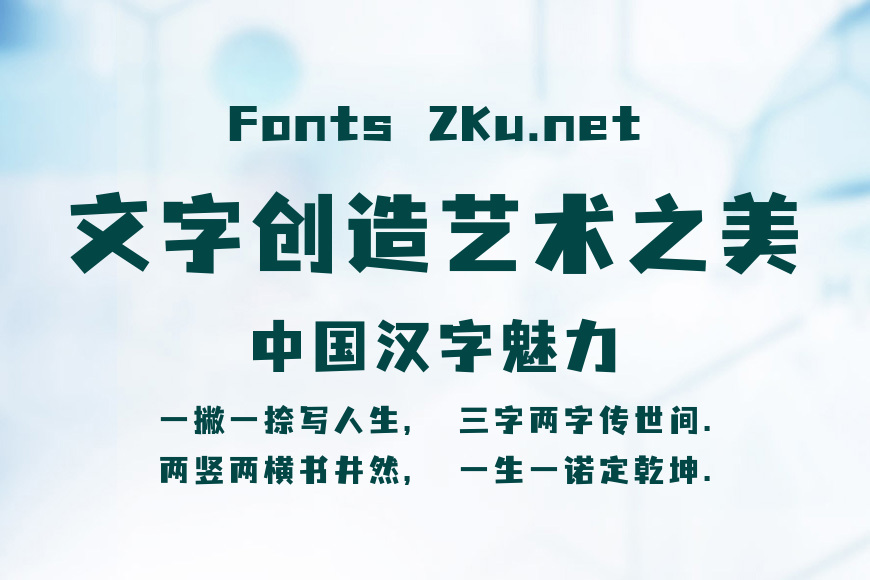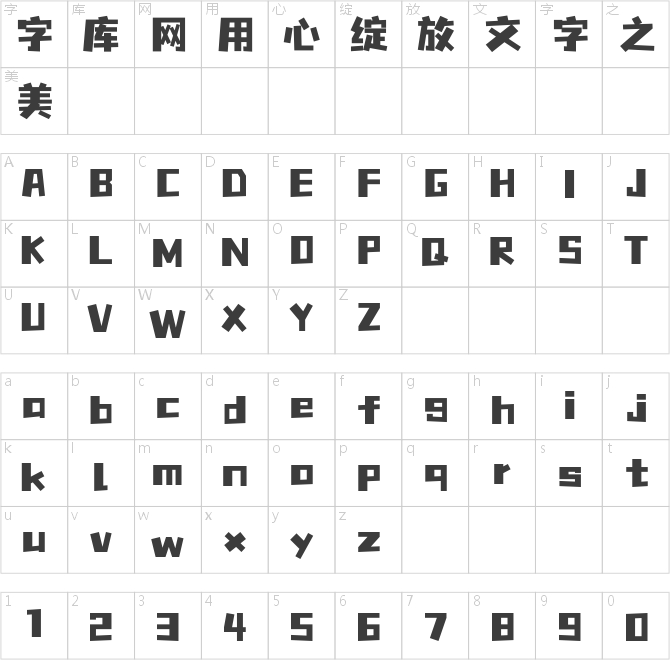
优设字由棒棒体
优设字由棒棒体介绍
优设字由棒棒体的名称是字由提议的三个方向选择而来,初始的三个版本是棒棒体、CP 体、联合体,最终经过讨论确定为棒棒体。一方面是寓意 2021 年工作棒棒,身体棒棒,新年棒棒。另一方面,由于字体本身的结构比较像棍子组成的笔划,棒棒体听起来也有一种轻松可爱的感觉,和字体的整体感觉比较相符。
设计初衷
我们前两款字体分别偏力量和柔美,在第三套字的制作上,特别想出一款风格截然不同、且广泛适用于日常工作需求的标题字。
经过和字由的多次讨论,结合它最终的使用场景,最后从延伸出的 3 个不同版本中,敲定了这款可爱风的字体雏形。